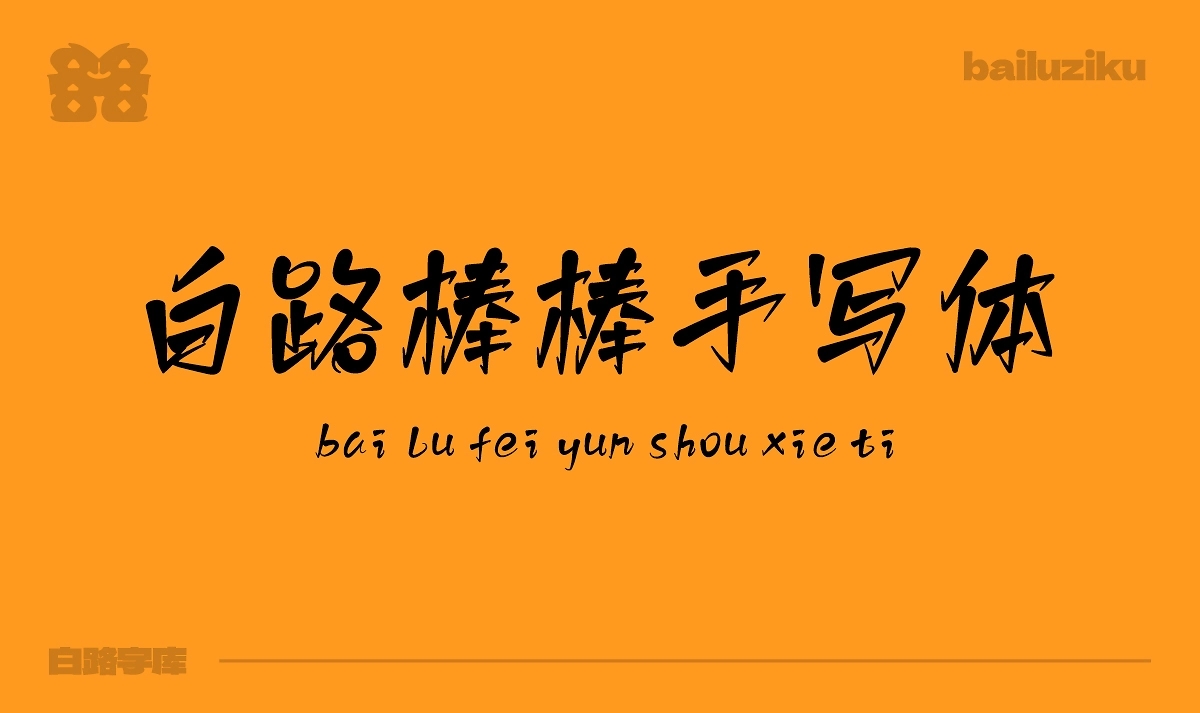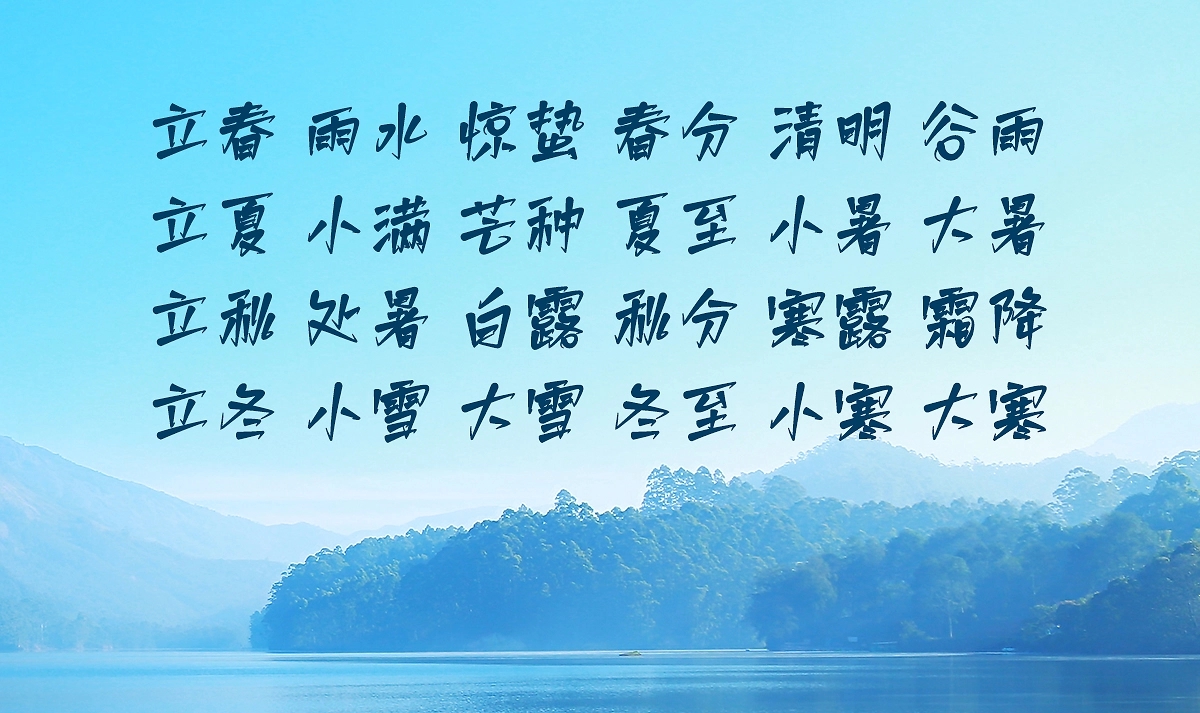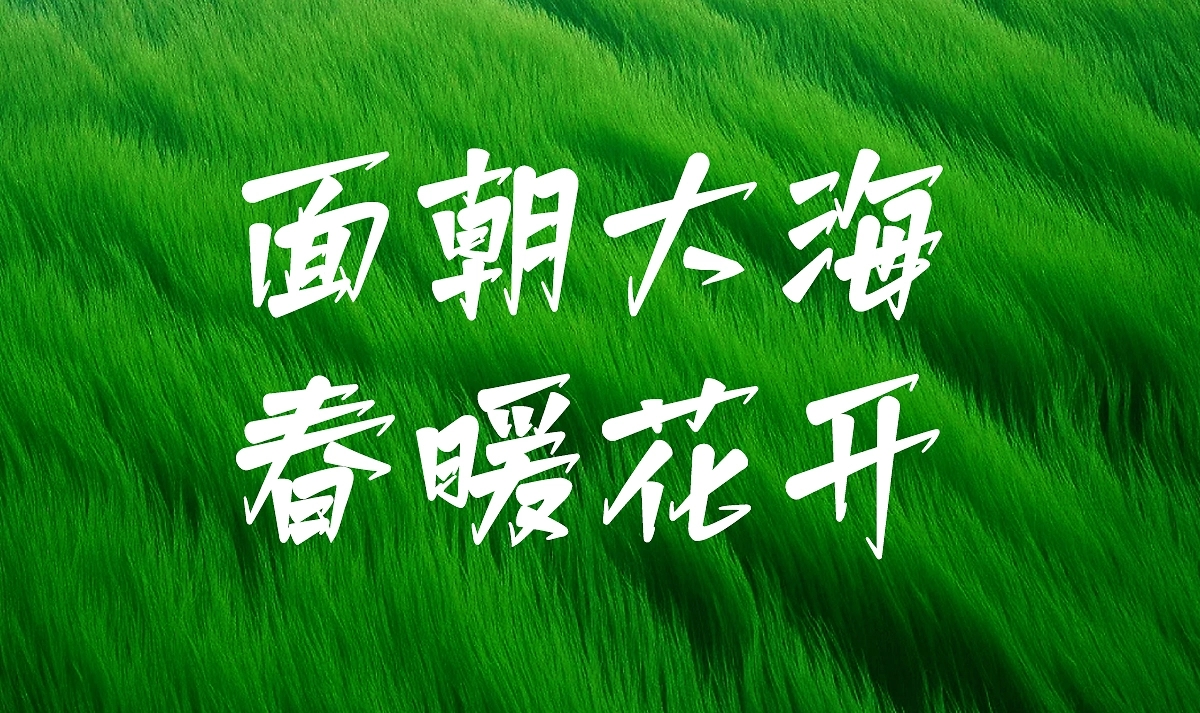
白路棒棒手写体
白路棒棒手写体,这款字体结构工整、笔画清晰,兼顾美观与易读性,适用于标题、正文、海报、包装、LOGO 等多种场景。字形优雅稳定,风格百搭耐看,适配日常排版与创意设计,让文字呈现更舒适、更具质感。白路棒棒手写体一笔一画,皆是细节,以均衡的比例、流畅的线条打造舒适视觉体验,字形端正大气,风格简约现代。无论是商业设计、品牌宣传还是日常排版,都能轻松驾驭,让文字更有格调与力量。白路棒棒手写体字体下载。
自己手写一款字体,字符加数字,英文及标点符号共6796个字符,该字库风格为手写偏文艺,喜欢的可以下载使用。    已注册版权,附件有字体文件。
作者:山人白路